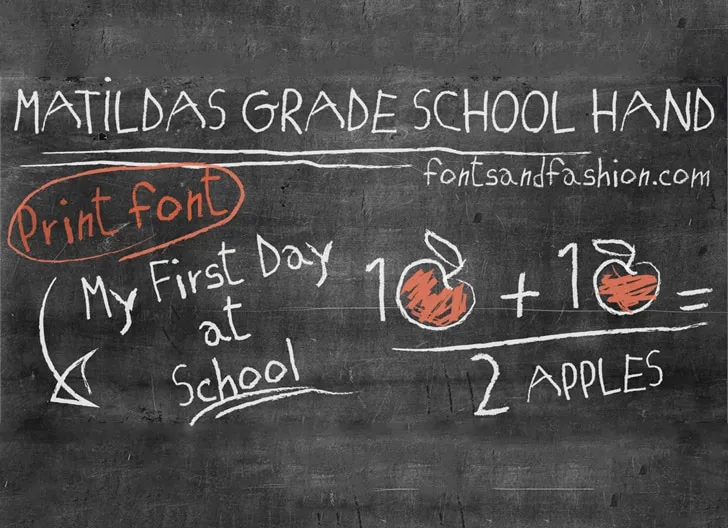
MATILDAS GRADE SCHOOL HAND Font
A Fontsandfashion está oferecendo a você uma fonte handwritten exclusiva chamada ‘MATILDAS GRADE SCHOOL HAND’. Esta fonte foi criada para ajudar qualquer designer a dar um toque especial às suas criações digitais, especialmente quando se trata de impressões gráficas pessoais. Com o seu estilo educacional e amigável, a MATILDAS GRADE SCHOOL HAND é perfeita para aqueles que gostam de criar mensagens únicas ou personalizadas em desenhos animados infantis. O designer, Fontsandfashion, mantém sua comunidade atualizada através das suas redes sociais. Você pode segui-los no Facebook e Pinterest para ver novidades recentes e promocionais. Além disso, outros designers podem encontrar mais opções da mesma fonte ou semelhantes em outras plataformas de design gráfico. Através desta página de download gratuita, você pode experimentar o poder do MATILDAS GRADE SCHOOL HAND para criar mensagens memoráveis e estilos únicos. Seja criando um logotipo personalizado, uma lembrança de aniversário ou até mesmo uma simples saudação escrita à mão na sua próxima criação gráfica, a Fontsandfashion e sua fonte oferecem a você uma excelente opção para expressar seu próprio estilo.